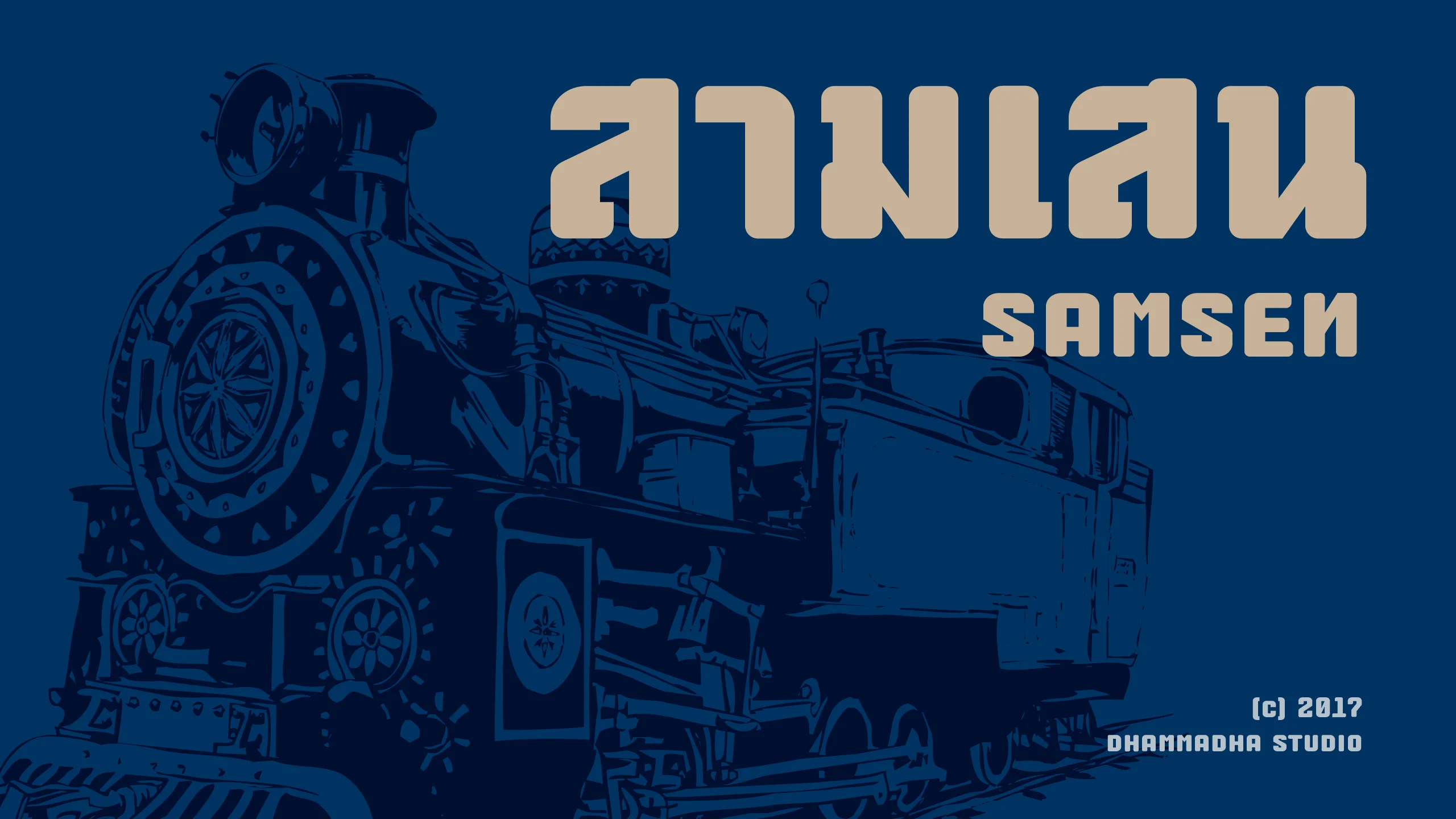
"สามเสน | samsen" คือผลงานที่ได้รับแรงบันดาลใจจากเอกลักษณ์อันเหนือกาลเวลาของป้ายสถานีรถไฟสามเสน โดยเริ่มต้นจากการขีดเขียนบันทึกเรื่องราวการเดินทางผ่านตัวอักษรลงในสมุดจด ฟอนต์ชุดนี้ตั้งใจถ่ายทอดรูปลักษณ์ดั้งเดิมของป้ายต้นแบบไว้อย่างครบถ้วน แล้วนำมาขัดเกลาด้วยแนวคิดการผสมผสานความเก่าแก่เข้ากับความร่วมสมัย ผลลัพธ์ที่ได้คือตัวอักษรที่มีกลิ่นอายของประวัติศาสตร์ แต่ยังคงความเรียบเท่และส่งต่อความรู้สึกที่เปี่ยมด้วยเรื่องราว เหมาะสำหรับงานที่ต้องการความคลาสสิกที่มีชั้นเชิง ในส่วนของตัวอักษรละติน เรายังคงรักษาภาพลักษณ์เฉพาะตัวไว้อย่างเหนียวแน่น โดยเฉพาะการออกแบบให้ตัวพิมพ์เล็ก (Lowercase) มีรูปลักษณ์ที่ล้อไปกับตัวพิมพ์ใหญ่ (Uppercase) เพื่อสร้างความต่อเนื่องลื่นไหลในเชิงดีไซน์ พร้อมทั้งบรรจุชุดอักษรไว้อย่างครบครันทั้งตัวพิมพ์ใหญ่ ตัวพิมพ์เล็ก และ Small Caps เพื่อความสมบูรณ์แบบในการใช้งาน "สามเสน | samsen" จึงเป็นเครื่องมือสื่อสารที่ช่วยสะท้อนความใส่ใจในรายละเอียดและเพิ่มเสน่ห์อันเป็นเอกลักษณ์ให้กับทุกผลงานออกแบบของคุณ